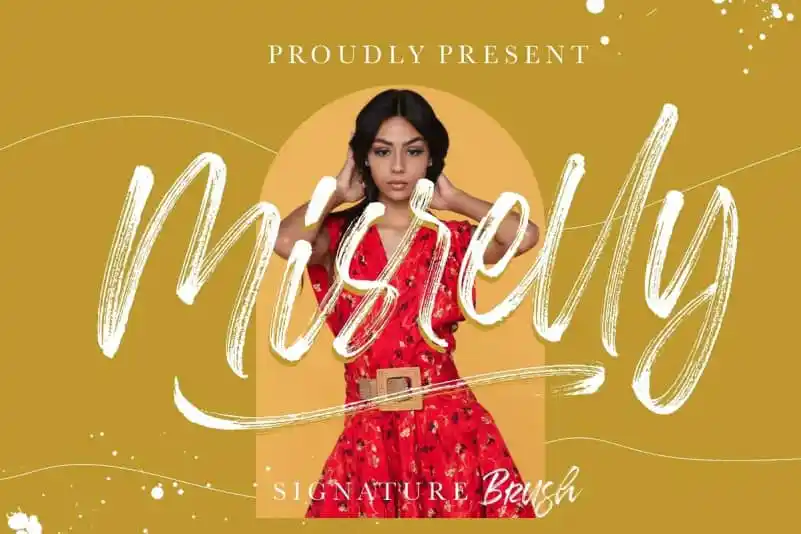
Misrelly Brush Font – Fonte Grátis
Misrelly Brush Font
A Misrelly Brush Font é uma opção perfeita para quem busca dar um toque único a seus projetos digitais e impressos. Com sua forma delicada e personalizada, essa tipografia retrata uma autenticidade genuína que se torna irresistível quando aplicada em textos de marca, identidades de logomarca, designs de casamentos ou até mesmo publicações nas redes sociais. Seu charme casual e aconchegante é ideal para adicionar uma pitada de personalidade aos produtos, como embalagens, etiquetas e materiais promocionais. Além disso, ela também se destaca perfeitamente em imagens fotográficas, marca d’água, convites e material de estação, garantindo que todos os seus projetos fiquem ainda mais especializados. Com o Misrelly Brush Font da 99designs, você pode criar designs únicos sem sair de casa.